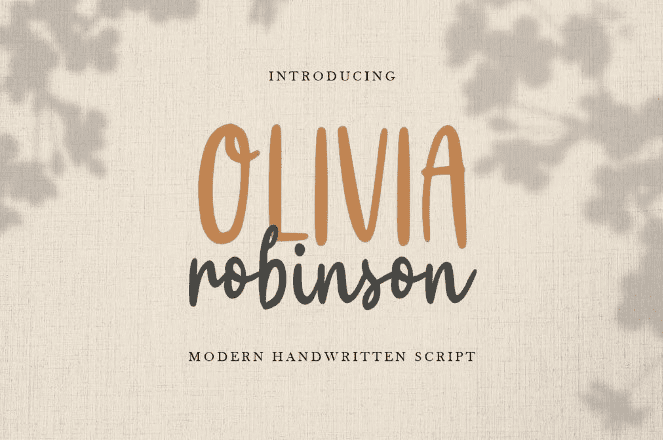
Название: Olivia Robinson Font
Оливия Робинсон - рукописный шрифт с естественным, веселым, современным и приятным стилем.
Этот шрифт создал специальные шрифты для смешных проектов, готовые к использованию в брендинге, социальных сетях, логотипе и многих других, которые нуждаются в очаровательных штрихах.